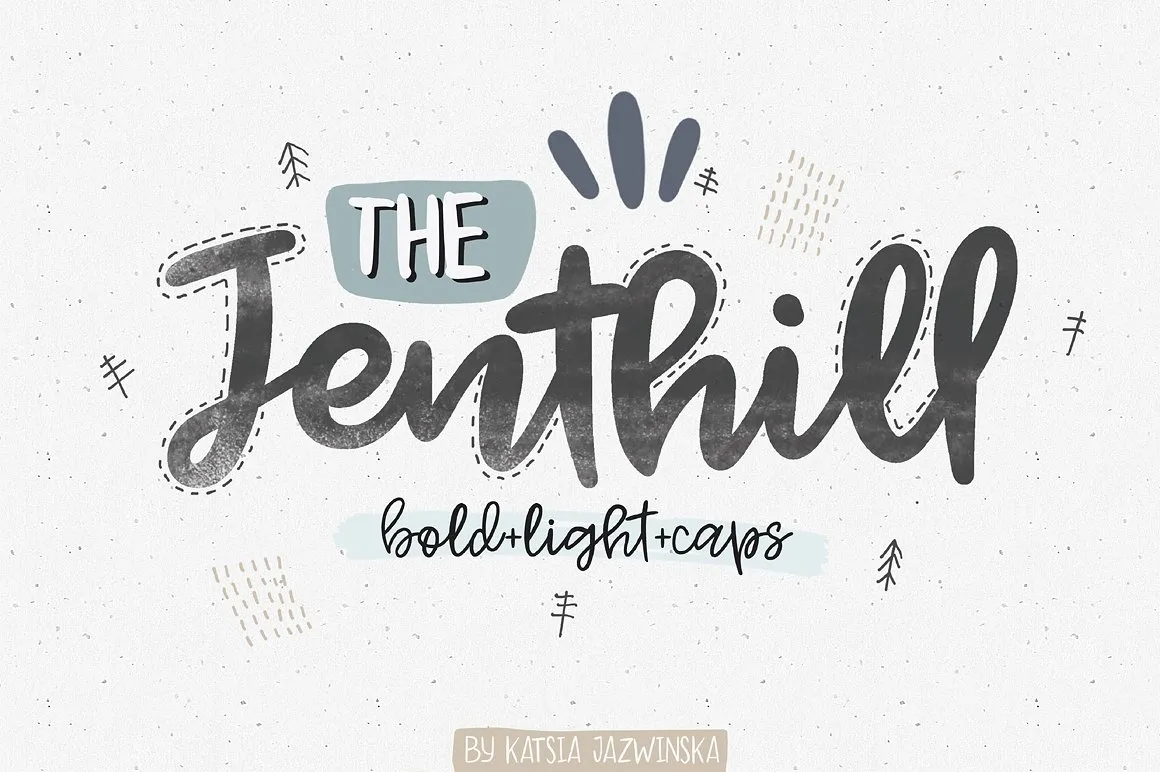
Jenthill Script Font – Download Grátis
A Jenthill Script Font é uma família de tipo script desenvolvida pelo designer Katsia Jazwinska. Ela é perfeita para incorporar um estilo manuscrito na sua próxima criação gráfica, seja ela uma identidade visual, uma apresentação ou qualquer outro projeto que precise de elegância e sofisticação. Com quatro estilos distintos – a Jenthill original, Jenthill Light, uma versão mais delicada da primeira opção, e dois tipos maiúsculos, Jenthill Caps e Jenthil Light Caps – esta família de fontes é perfeitamente adequada para se tornar o destaque do seu design. Obrigado à designer por compartilhar este belo conjunto de recursos gráficos que eleva qualquer projeto para o próximo nível.